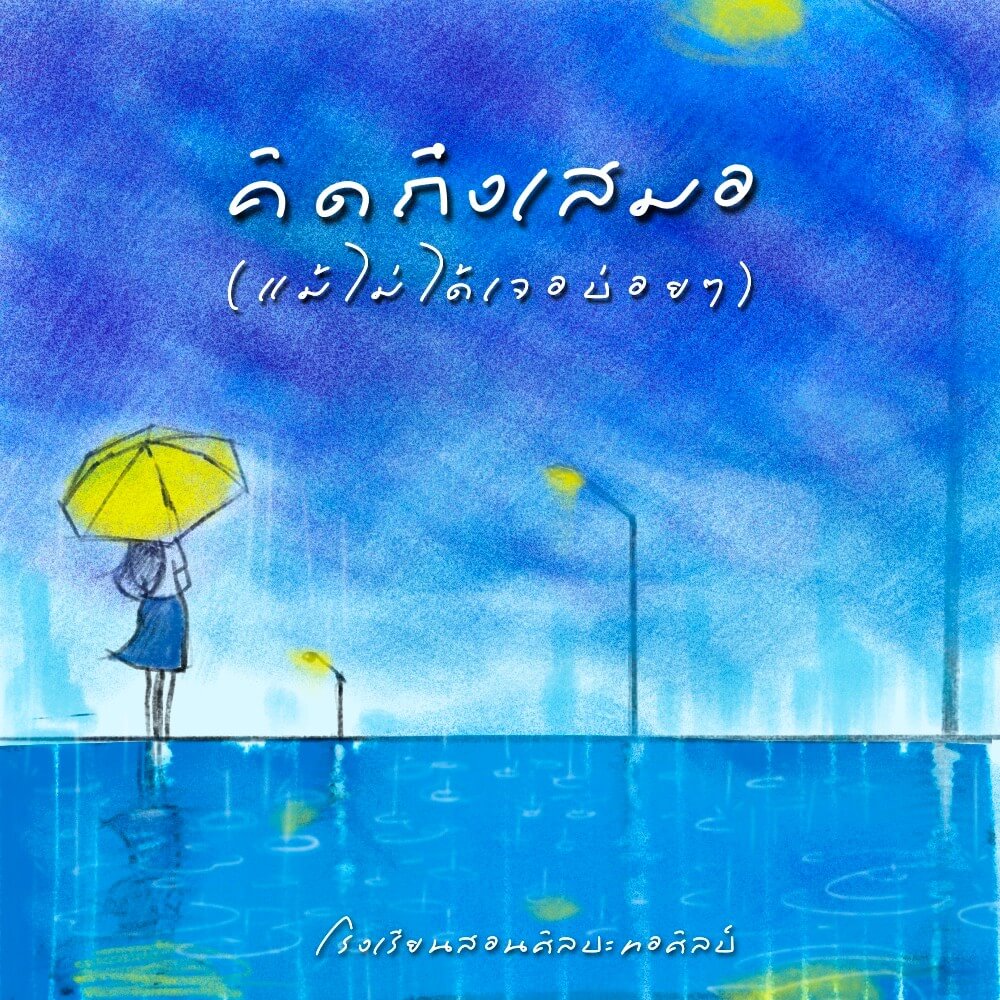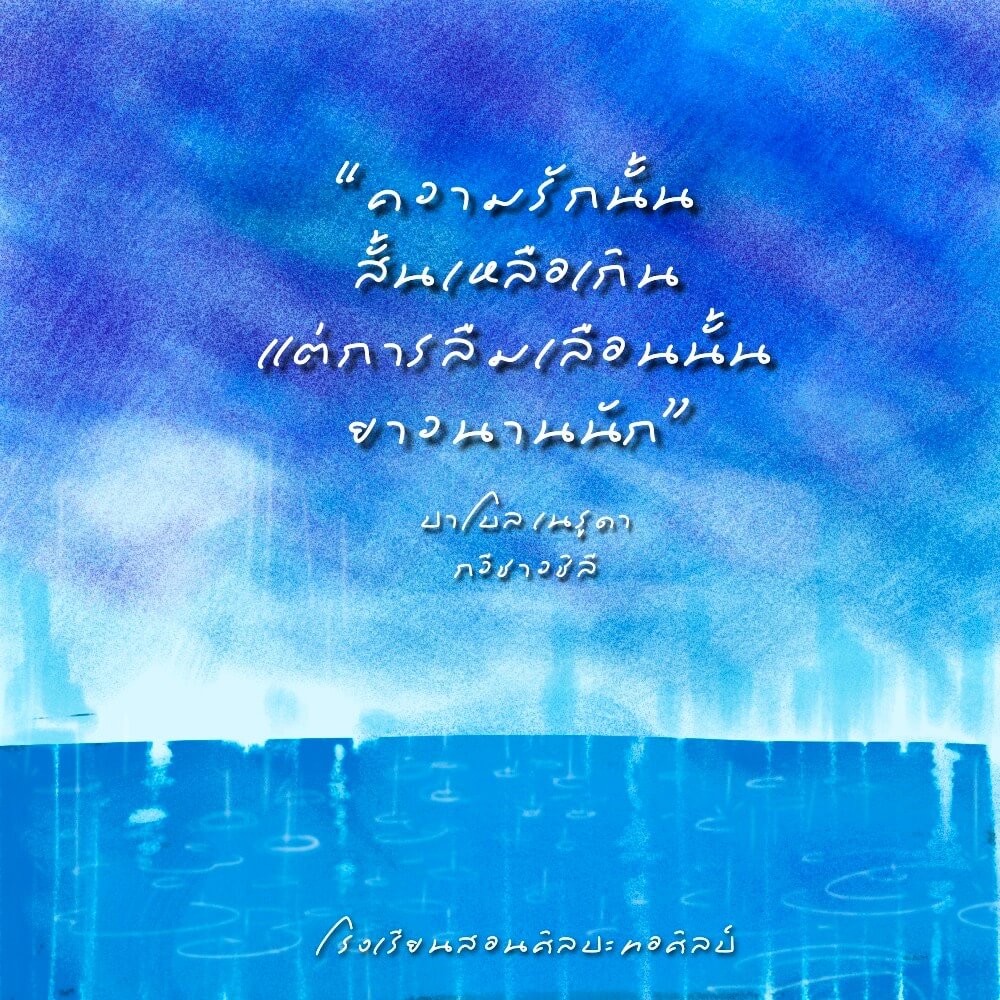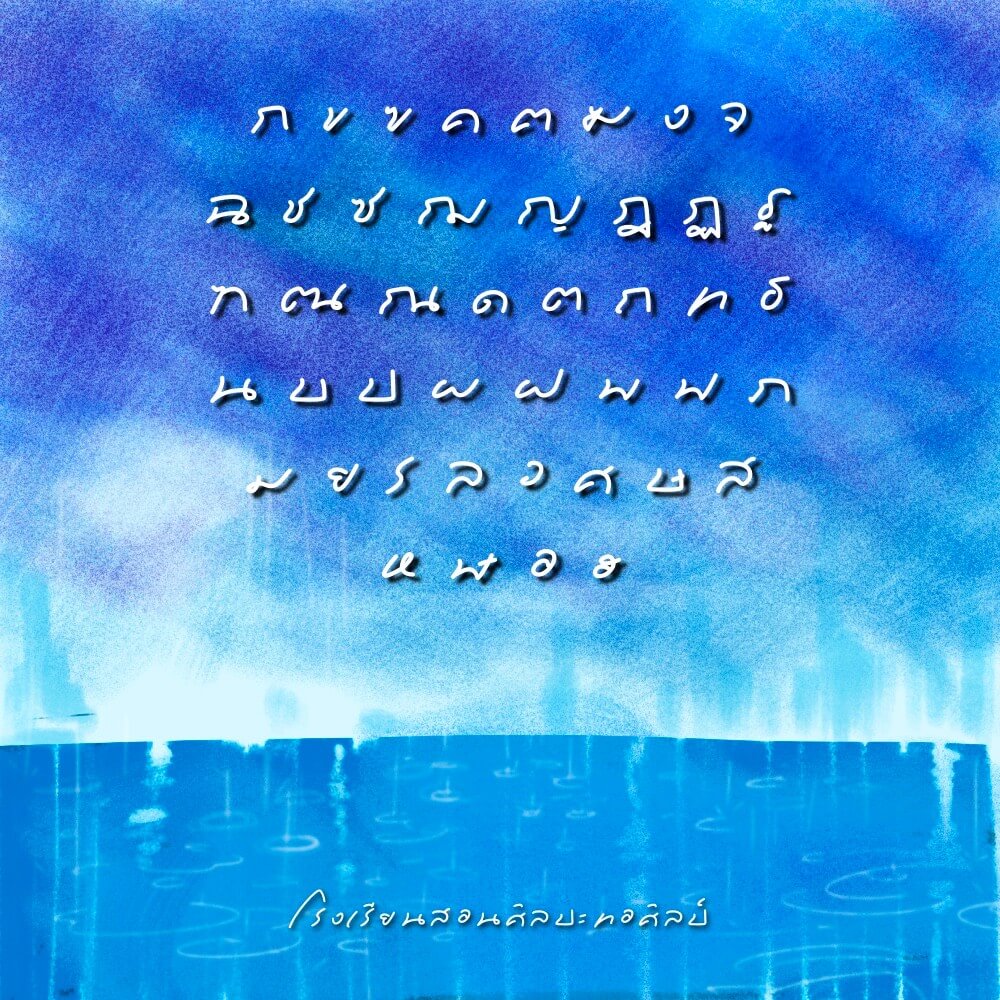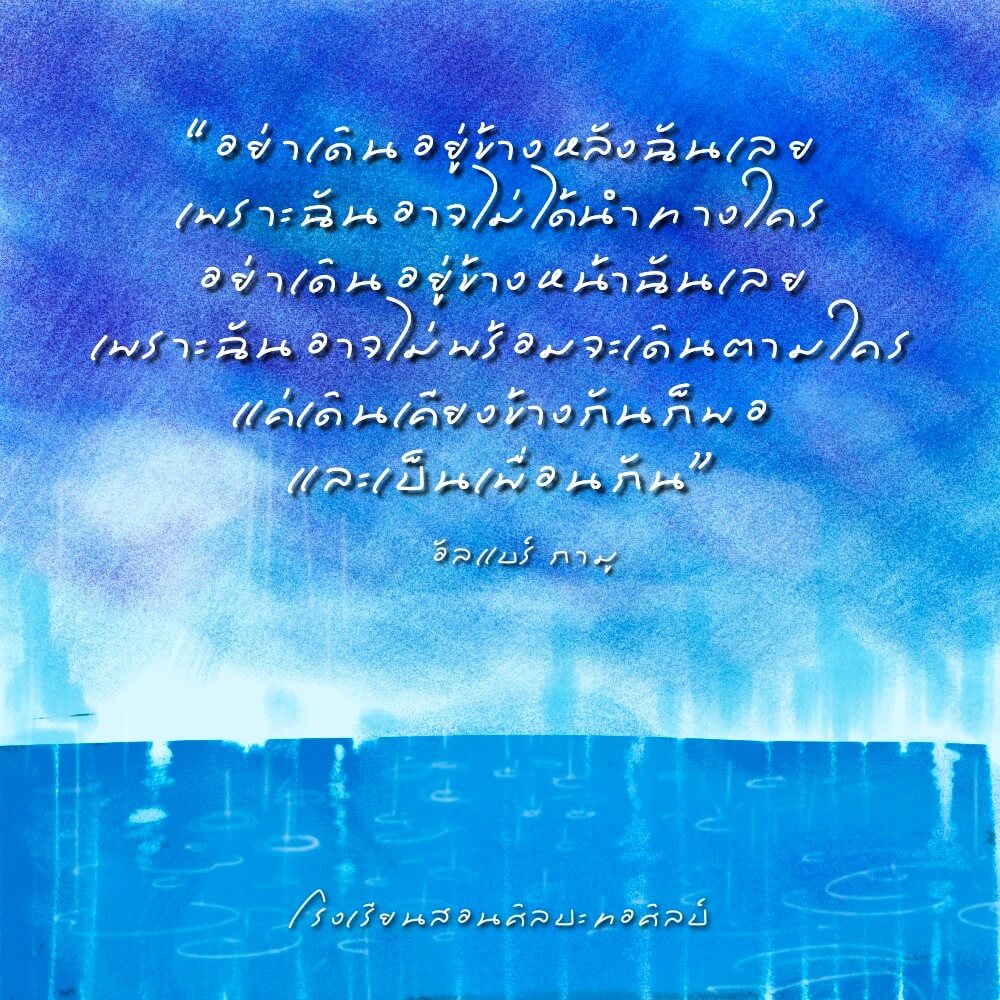
ฟอนต์ “ทอศิลป์ คิดถึงเสมอ” โดย โรงเรียนสอนศิลปะทอศิลป์ เป็นฟอนต์ลายมือเขียนหวัดนิดหน่อย เลยจัดระยะระหว่างตัวหนังสือให้ห่างจากกันเล็กน้อย เอาไปใช้โพสต์ประกอบคำคมแรงบันดาลใจหรือข้อความสั้นๆ แบบเป็นกันเองจะเหมาะมากๆ
ทอศิลป์ คิดถึงเสมอ (Torsilp Khitthueng Samoe)